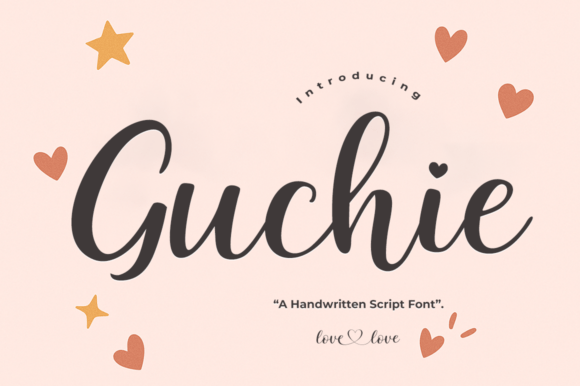
Guchie
Guchieのような高品質の素材をお探しの場合、このプレミアムパッケージはクリエイティブなプロジェクトに素晴らしい選択です。
精密に作られたGuchieは、クリーンなベクター、滑らかなタイポグラフィ、そして安心のための商用ライセンスを提供します。
POD(オンデマンド印刷)製品、結婚式の招待状、またはソーシャルメディアのグラフィックを作成している場合でも、Guchieは理想的です。